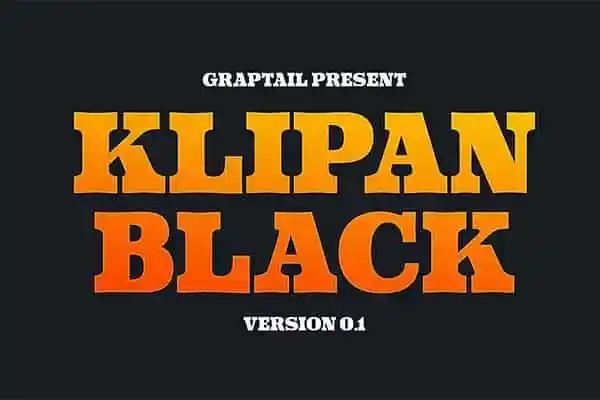
Descubra a essência da cultura western com Klipan Black Font. Inspirado nos tipos antigos dos cowboys e estilos western, essa fonte robusta e rústica combina duas largas linhas para criar designs únicos. Ideal tanto para logotipos quanto para capas de loja ou textos em destaque, este tipo exala um ar vintage e antigo, perfeito para ambientes que valorizam estilos western e arte retro-pop. O Klipan Black Font é uma escolha ideal se você está buscando dar um toque nostálgico a seus projetos digitais ou impressos. Com uma versão em letras maiúsculas e minúsculas, você pode combiná-las de maneiras criativas para criar designs impecáveis que remetem aos tempos de cowboy e ao revival cultural do século XXI. Não hesite em experimentar Klipan Black Font na sua próxima criação visual para capturar a essência da cultura western no seu design.